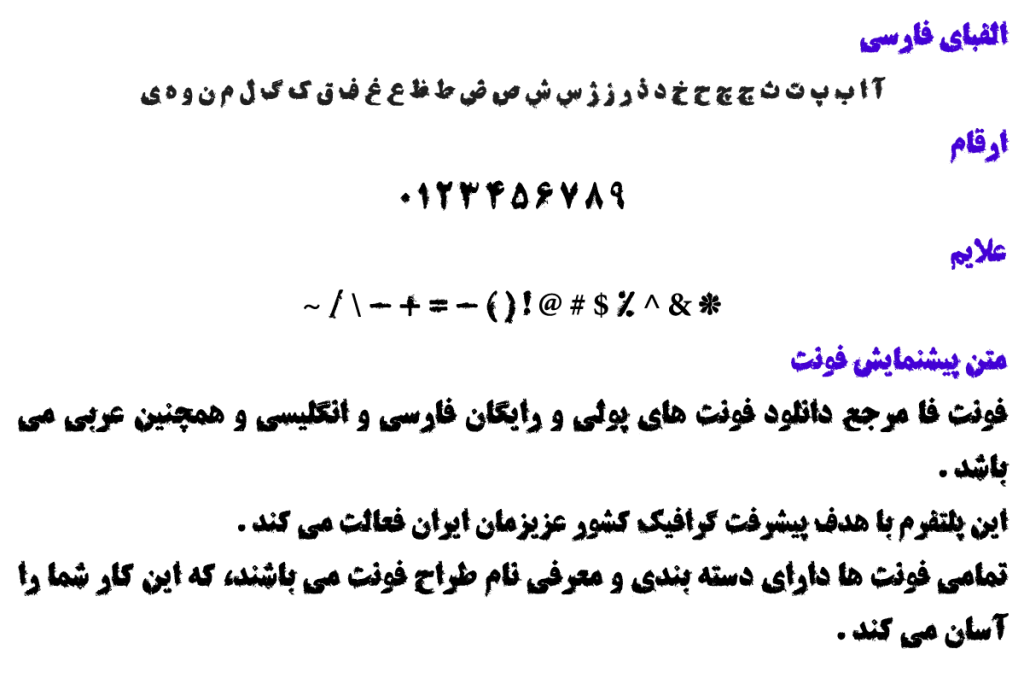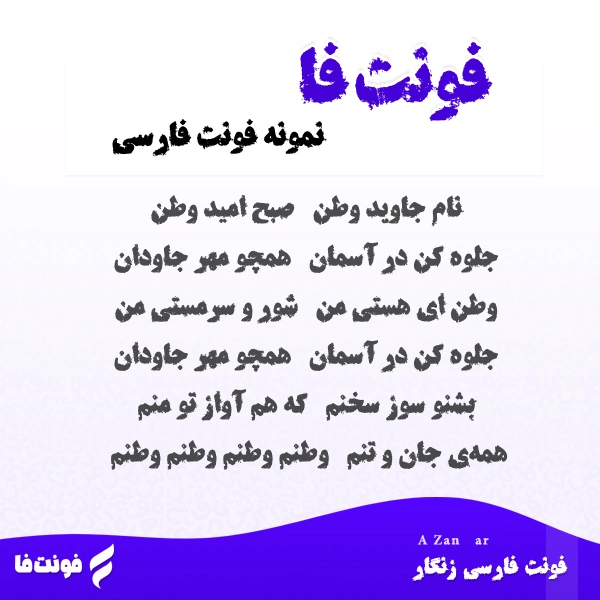
فونت فارسی زنگار – A Zangar
نوع فونت: فونت گرافیکی
توضیحات و معرفی فونت زنگار
فونت فارسی زنگار ( A Zangar ) از مجموعه فونت های آزاد می باشد، و نیز نوع فونت گرافیکی می باشد.
فونت خوشگل مربوط توسط روح الله گیتی نژاد در سال 1390 طراحی و ساخته شده است.
و نیز فونت A Zangar در یک وزن پر رنگ است.
در تصویر زیر می توانید شعر زیبای «وطنم» را که با این قلم نوشته شده، تماشا کنید.